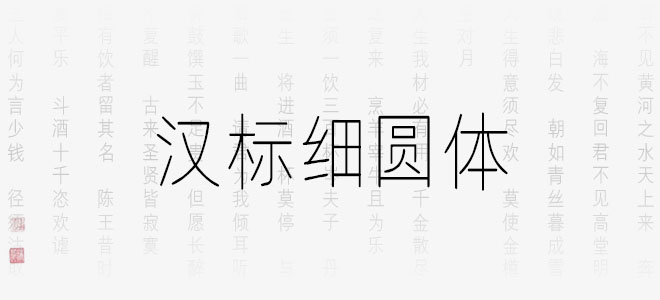
漢標(biāo)細(xì)圓體字體是一款由漢標(biāo)字庫(kù)推出的藝術(shù)字體,該字體線條看上去非常的細(xì),字型比較的圓潤(rùn)流暢,整體的設(shè)計(jì)風(fēng)格舒展纖柔,適合一些跟女性、兒童相關(guān)的設(shè)計(jì)方面,歡迎喜歡漢標(biāo)細(xì)圓體的朋友前來(lái)下載使用。
漢標(biāo)細(xì)圓體